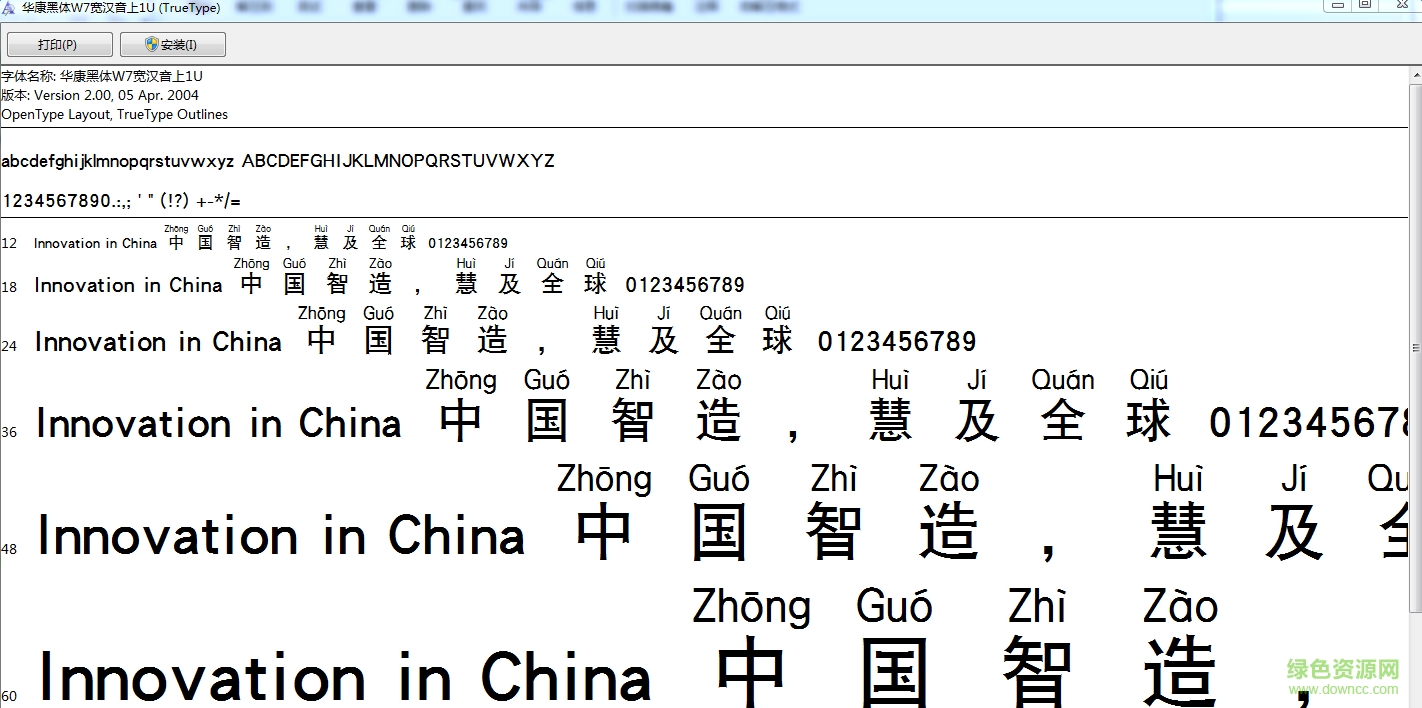
華康黑體W7寬漢音上U字體是一款華康類w7寬漢音黑體字體軟件,黑色的字體給人非常正規(guī)的感覺,深受廣大年輕人的喜愛,還有更多好看字體盡情期待,歡迎到綠色資源網(wǎng)下載體驗(yàn)!
華康黑體W7寬漢音上U是一款華康類w7寬漢音的黑體字,字體效果比較黑,喜歡黑體字的朋友可以下載使用看看效果如何。